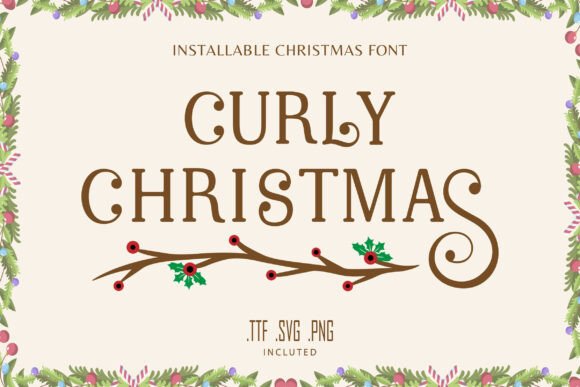
Curly Christmas
適切なデザイン要素を見つけるのは難しい場合がありますが、Curly Christmasは作品を即座に引き立てる優れたコレクションを提供します。
精密に作られたCurly Christmasは、クリーンなベクター、滑らかなタイポグラフィ、そして安心のための商用ライセンスを提供します。
POD(オンデマンド印刷)製品、結婚式の招待状、またはソーシャルメディアのグラフィックを作成している場合でも、Curly Christmasは理想的です。